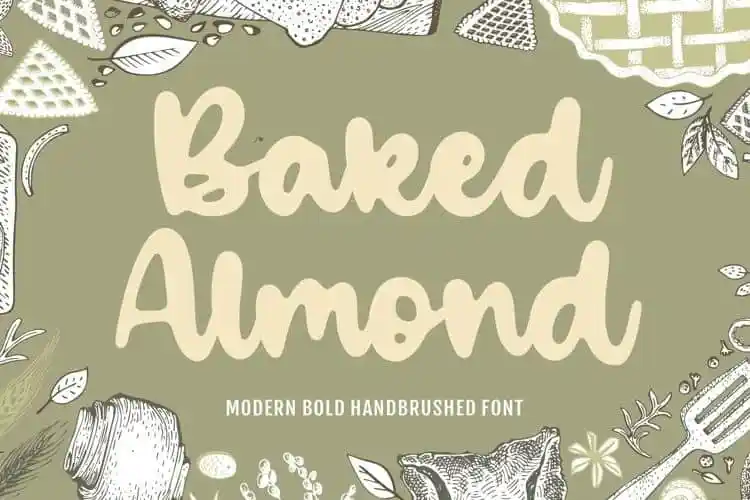
Baked Almond Handbrushed Font – Download Grátis
A fonte Baked Almond Handbrushed é perfeita para projetos que exigem um toque delicado e único, seja para embalagens de produto, criação de marca, revistas, mídia social, até mesmo para destacar frases acima de um fundo. Ideal tanto para os mais elaborados quanto os simplesmente criativos, esta fonte traz uma textura suave e aveludada que encaixa-se perfeitamente com temas como produtores de eventos, casamentos ou qualquer outra área em que você deseje expressar as palavras acima do fundo de um projeto. Seja ela um toque discreto na marca de uma empresa ou o destaque da frase principal de uma postagem no Instagram, a Baked Almond Handbrushed é uma escolha perfeita para quem busca uma fonte que combine elegância com um pouco de brilho casual e descontraído.